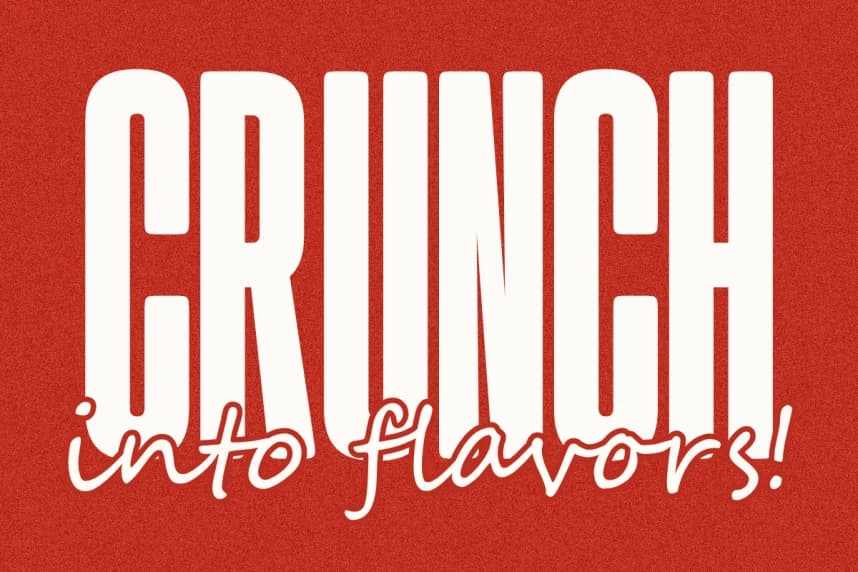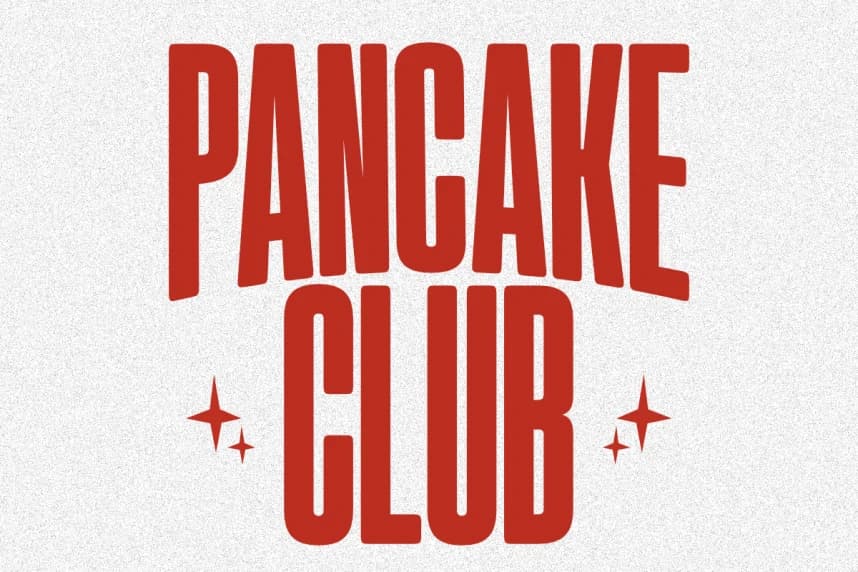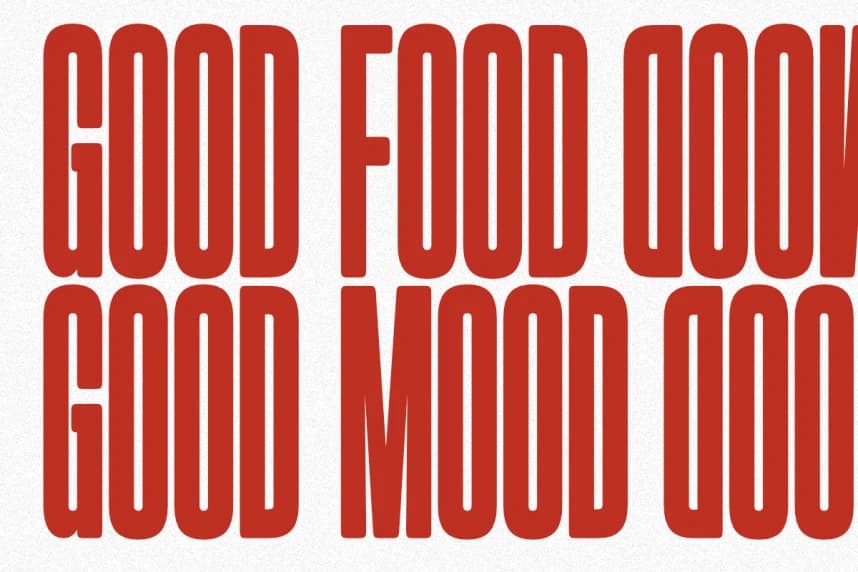
Nugget Font
Nugget Font, cesur ve çok yönlü bir retro sıkıştırılmış sans yazı tipidir; vintage nostaljik cazibeyi temiz, modern bir estetikle ustalıkla harmanlar. Yüksek etkiye sahip görsel anlatım için özel olarak tasarlanmıştır; uzun ve sağlam yapısı dikkat çekerken zarif bir görünümünü korur.
Nugget Font, cesur ve çok yönlü bir retro daraltılmış sans fontudur; vintage nostaljik çekiciliğini temiz, modern bir estetikle ustaca harmanlar. Özellikle yüksek etkili görsel hikâye anlatımı için tasarlanmıştır; uzun ve sağlam yapısı dikkat çekerken şık bir görünümü sürdürür.